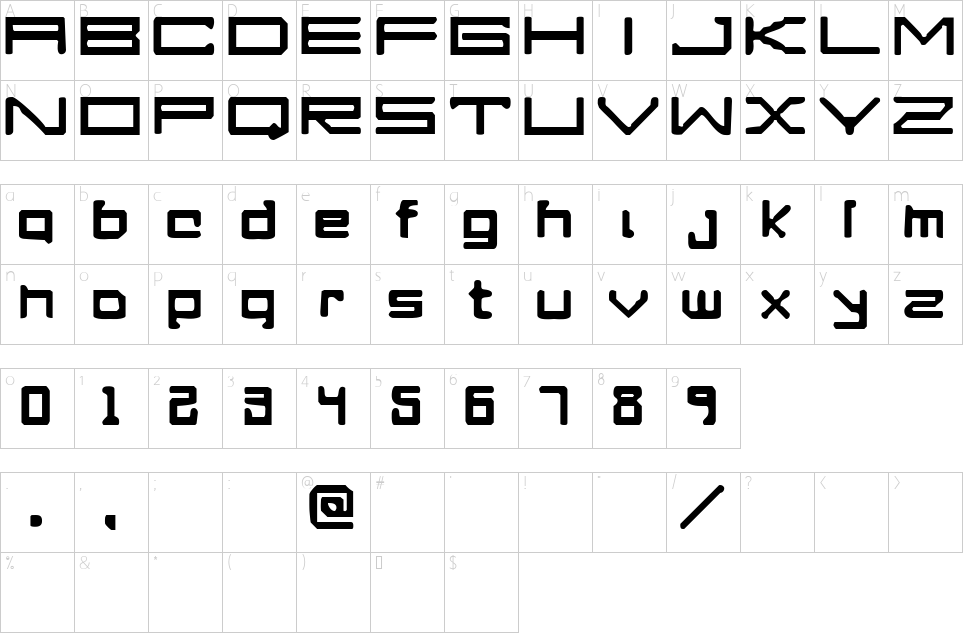
A fonte ‘A Perfect Drowning’ é uma escolha perfeita para quem procura uma fonte com um efeito atraente e envolvente. Desenvolvida pelo designer Mr Fisk, ela foi projetada com um design que remete a uma experiência poética e sensorial, especialmente a sensação de água, evocando emoções e ambientes ao mesmo tempo. Com o seu download de 8.717 vezes, é evidente que os artistas e designers buscam a sua elegância e originalidade. A fonte ‘A Perfect Drowning’ é uma excelente opção para aqueles que procuram um recurso de design que seja tanto atraente quanto funcional, trazendo vida e movimento a qualquer projeto. É uma fonte para todos aqueles que desejam adicionar uma camada atraente e poética ao seu design, seja em sites, design gráfico ou até mesmo em publicações impressas.